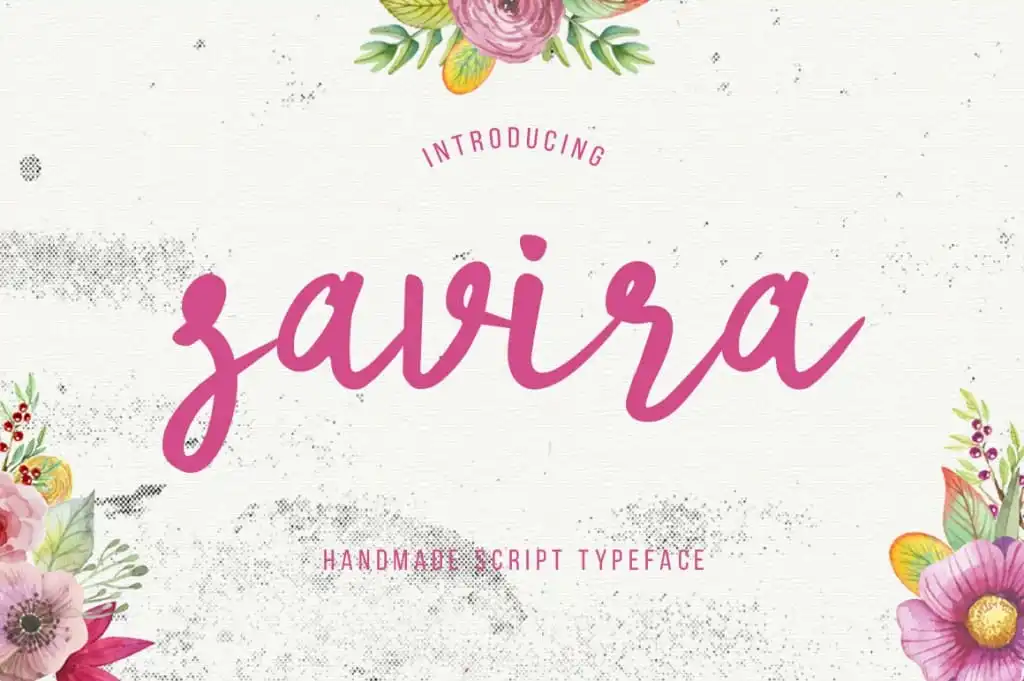
Savira Script Font – Download Grátis
A Savira Font é uma elegante tipografia handmade que combina harmoniosamente as nuances femininas e masculinas. Perfeita para uma variedade de projetos, essa fonte está se tornando um must-have para designers a procura de algo sofisticado e distintivo. Seja para logotipos icônicos, frases de propaganda em outdoors ou materiais de convites elegantes, a Savira oferece um estilo que transpira sofisticação e criatividade. Ideal tanto para editoriais como cartões de aniversário, sua personalidade única pode transformar qualquer projeto no qual seja aplicada. A Savira Font é uma escolha inteligente para quem busca um toque distinto em suas criações visuais.